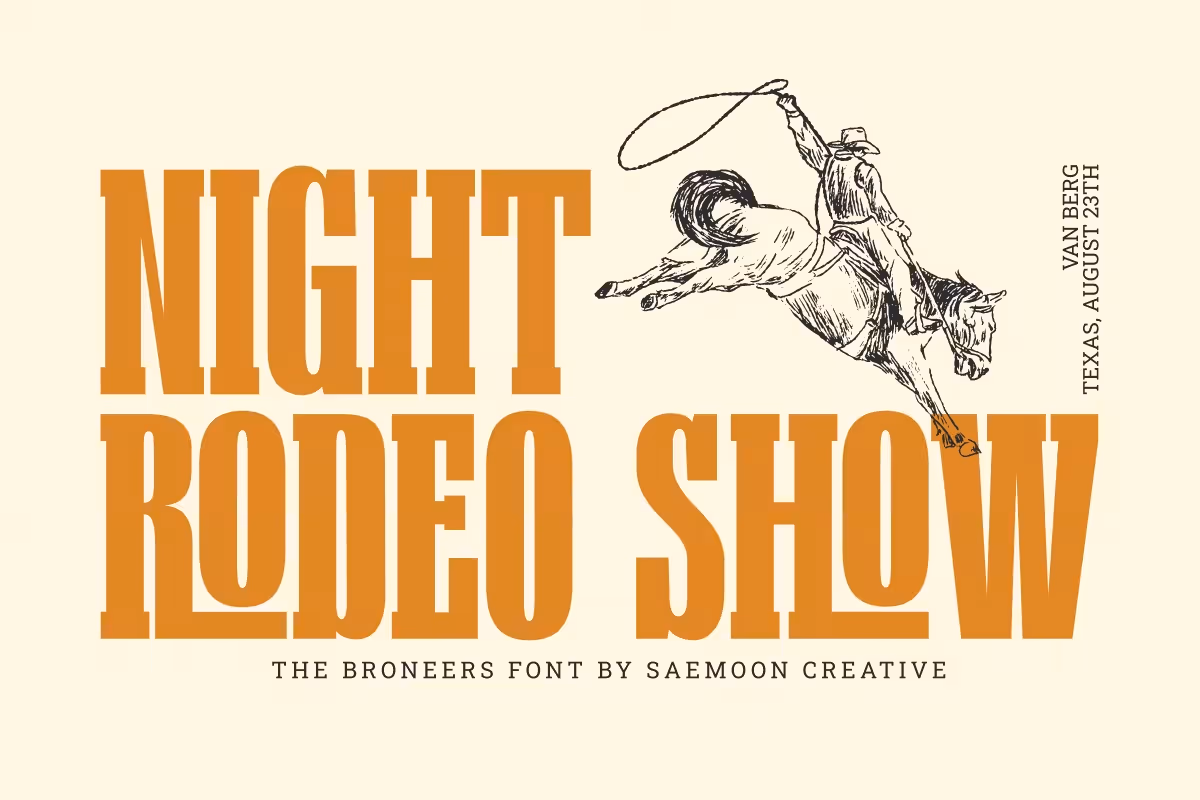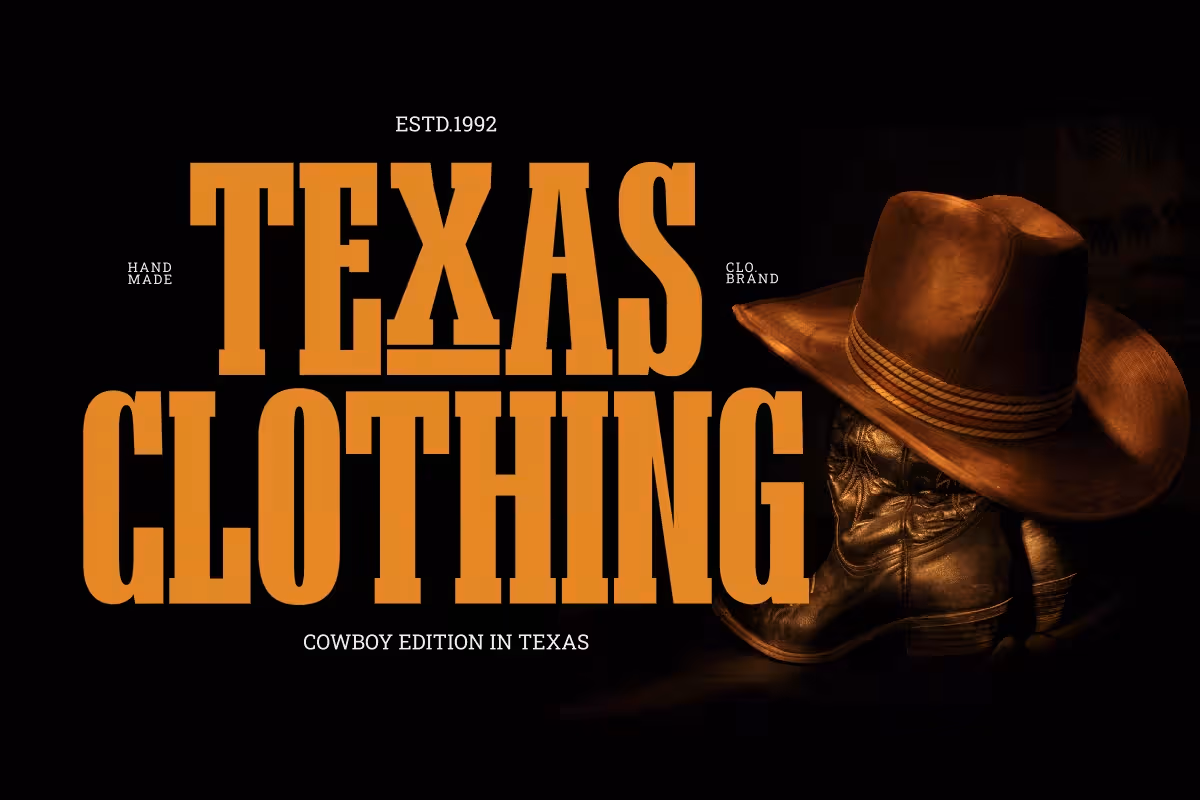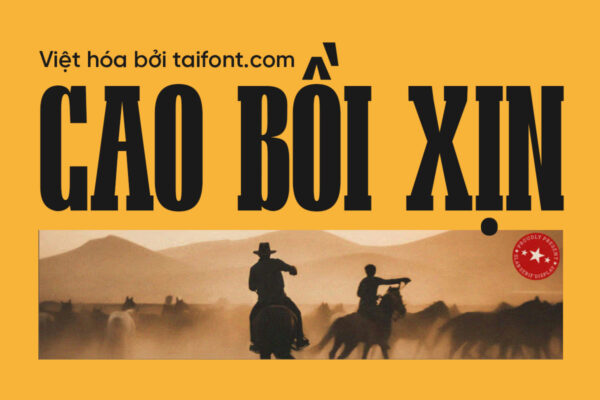
Giới thiệu về Font TF The Broneers Việt hóa
TF The Broneers Việt hóa là một font chữ độc đáo, tuy có chân (serif) nhưng lại mang phong cách thiết kế của font không chân (sans-serif) với nét mạnh mẽ, cứng cáp và đầy dứt khoát. Font này gợi cảm giác về sự phiêu lưu, khám phá của miền viễn Tây hoang dã, toát lên phong thái bụi bặm, kiên cường và đầy ấn tượng, lý tưởng để tạo điểm nhấn mạnh mẽ và thu hút mọi ánh nhìn, đặc biệt cho các thiết kế mang hơi hướng cao bồi.
Với đặc điểm thiết kế độc đáo, góc cạnh mạnh mẽ và khả năng gợi cảm xúc mạnh mẽ, The Broneers là lựa chọn hoàn hảo cho các ấn phẩm trong lĩnh vực giải trí, phiêu lưu và phong cách hoài cổ:
- Thiết kế poster vùng viễn Tây cao bồi: Hoàn hảo để sử dụng trên poster phim cao bồi, banner sự kiện lễ hội miền Tây, hoặc các ấn phẩm quảng bá liên quan đến chủ đề phiêu lưu, săn bắn. Font này giúp tạo không khí chân thực, kịch tính và đầy thách thức, đúng chất cao bồi.
- Thiết kế game và phiêu lưu: Lý tưởng cho logo game, tiêu đề, hoặc các ấn phẩm quảng bá các tựa game phiêu lưu, khám phá, hoặc sinh tồn. Nét chữ mạnh mẽ, cứng cáp của The Broneers sẽ làm tăng tính chân thực và độ “ngầu” cho trò chơi.
- Thiết kế cho các sự kiện đặc biệt: Phù hợp cho các sự kiện dã ngoại, cắm trại, hoặc các hoạt động cần một không khí mạnh mẽ, nổi bật và có chút bụi bặm.
- Thiết kế nhận diện thương hiệu: Có thể dùng cho các thương hiệu muốn truyền tải sự mạnh mẽ, cá tính và một chút hoài cổ đầy phong cách.
Với TF The Broneers Việt hóa, bạn có thể dễ dàng thổi hồn mạnh mẽ, sự độc đáo và cá tính vào các thiết kế, tạo ra những sản phẩm không chỉ đẹp mắt mà còn cực kỳ ấn tượng và có khả năng thu hút sự chú ý tối đa.
Font Việt hóa TF The Broneers